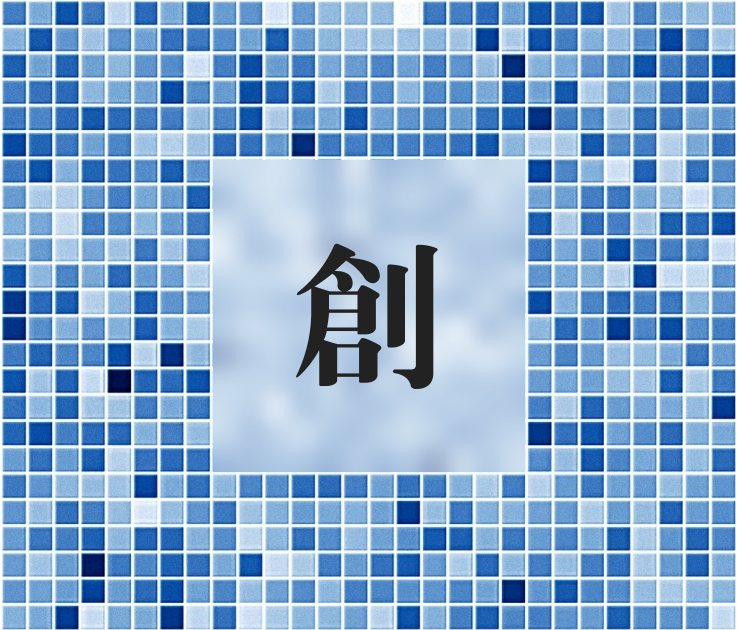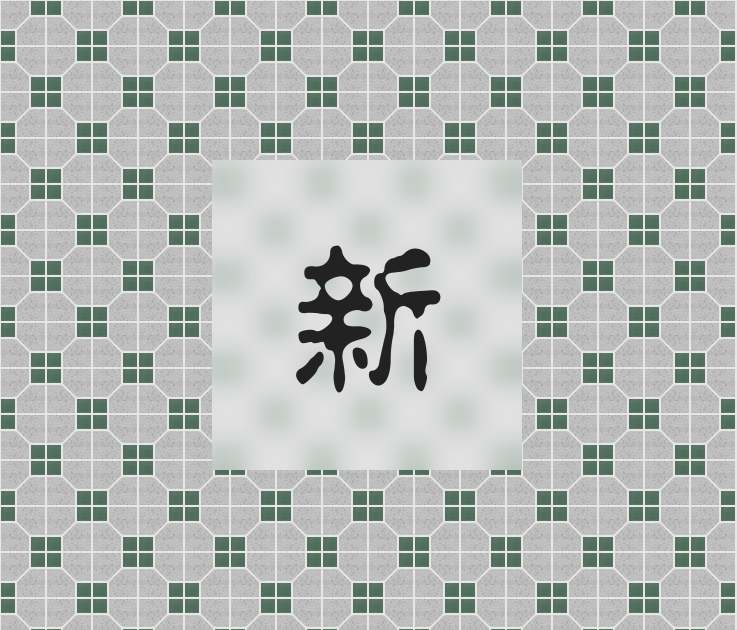
靈感緣起
解碼香港視覺,港風美學基因
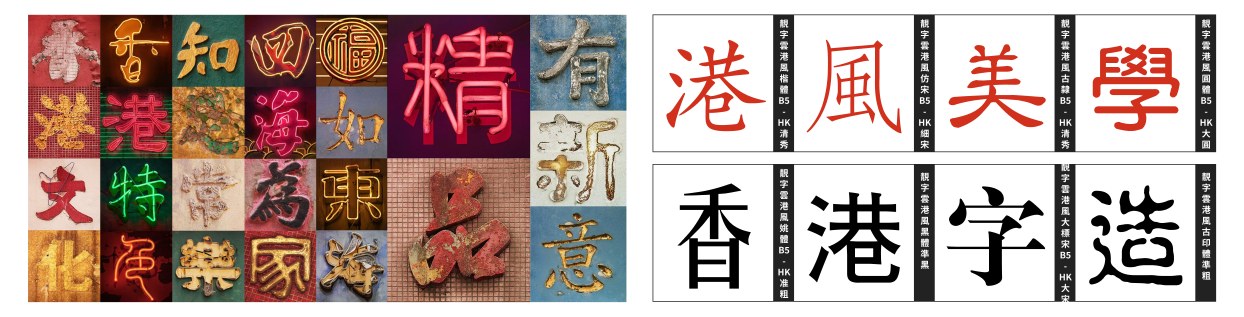
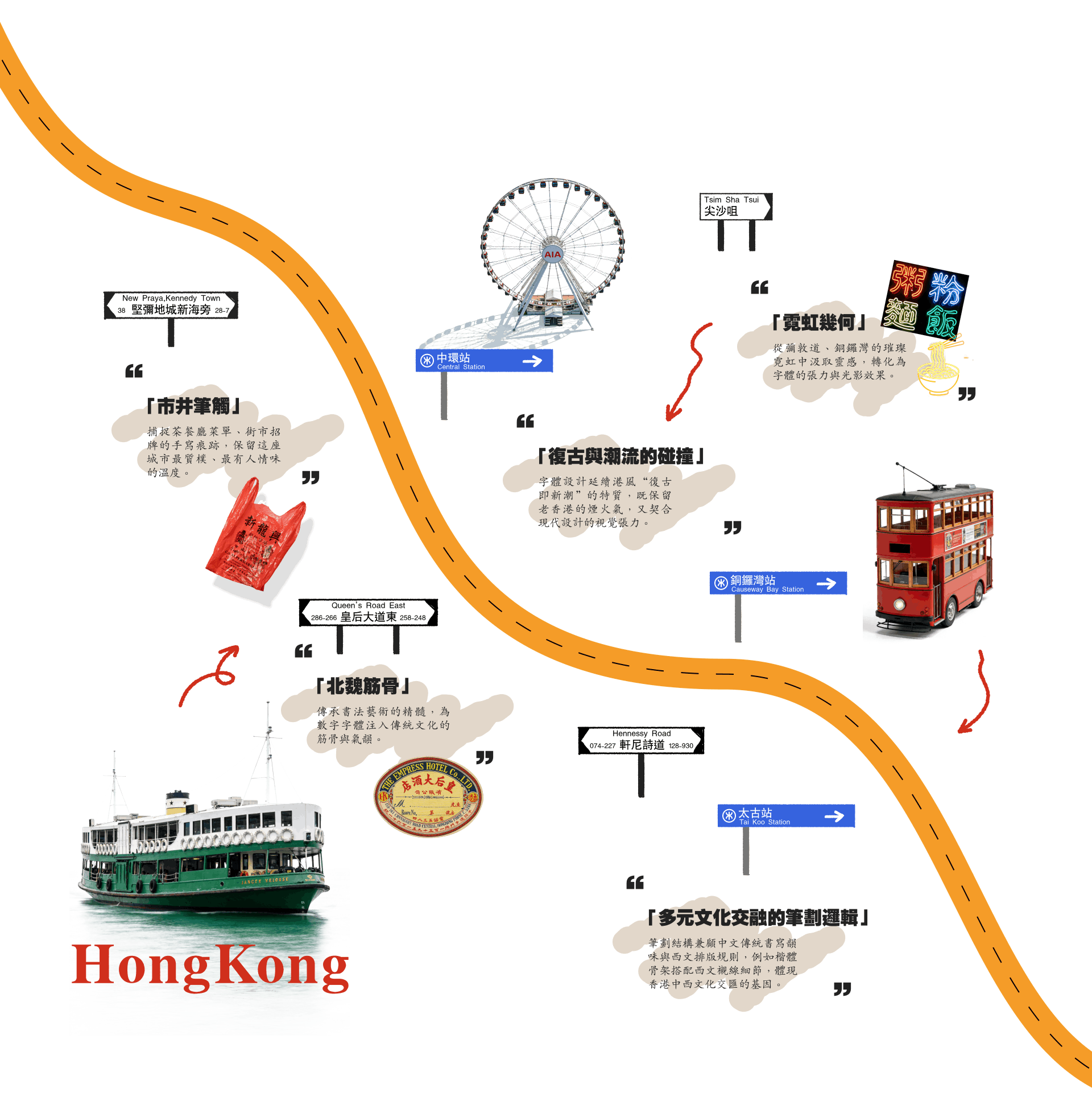
香港字造
靚字雲
字體設計延續港風“復古即新潮”的特質,既保留老香港的煙火氣,
又契合現代設計的視覺張力。
字載香江,形意共生
TYPE IN HONG KONG CREATIVE LAB(香港字造設計中心)是 NICETYPE (HK) LIMITED旗下的字體設計研發與文化創意中心。我們相信,字體不只是符號,而是香港城市記憶的載體。
我們從香港日常場景中汲取靈感,將這些流動在城市脈絡裡的視覺碎片,提煉為可系統化複用的字形資產。我們融合復古與潮流美學,再現港風街景的招牌排版韻味與霓虹燈牌的視覺張力,把茶餐廳的手寫溫度、彌敦道的燈管輪廓、老街市的字法節奏,一併收錄進字庫的基因序列之中。透過嚴謹的字形結構、字重階梯與多語本地化流程,持續探索「港風」在當代設計語境下的再詮釋——讓世界在字裡行間,重新閱讀香港。